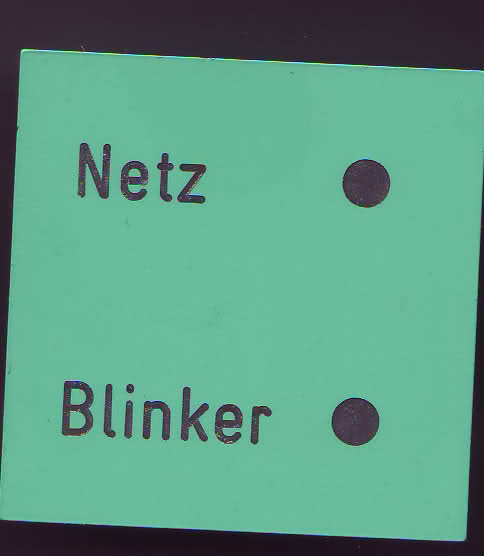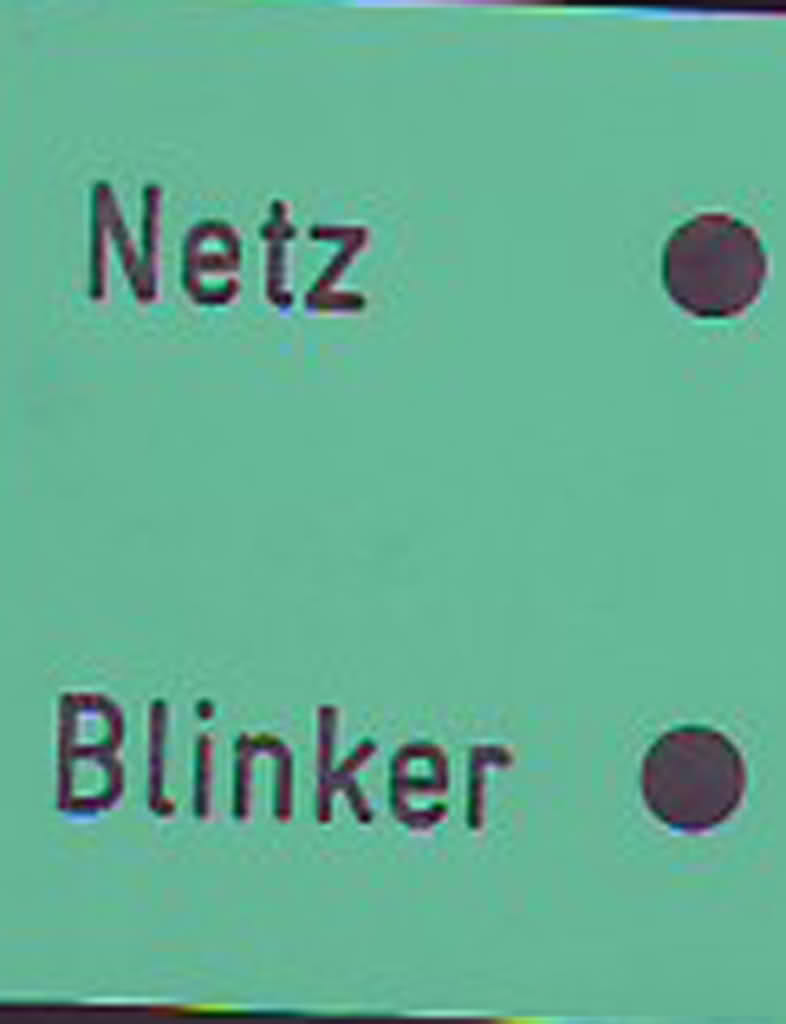
Schriftart gesucht.
Das schaut nach einer einzuegigen DIN Gravurschrift aus.
Das ist also keine Satzschrift.
Das ist ein Druck. Die Schrift hat so ein wenig Ähnlichkeit mit der DIN Engschrift, welche ich eigentlich auch für den Einsatz der Kappe erwartet hatte, nur die Rundungen am Anstrich und an den Enden gehören da irgendwie nicht hin. Falls es zur Bestimmung der Schrift hilft, die Kappen werden seit 40 Jahren so gedruckt, entworfen wurden sie in der DDR.
Hier ist das Bild nochmal in besserer Auflösung